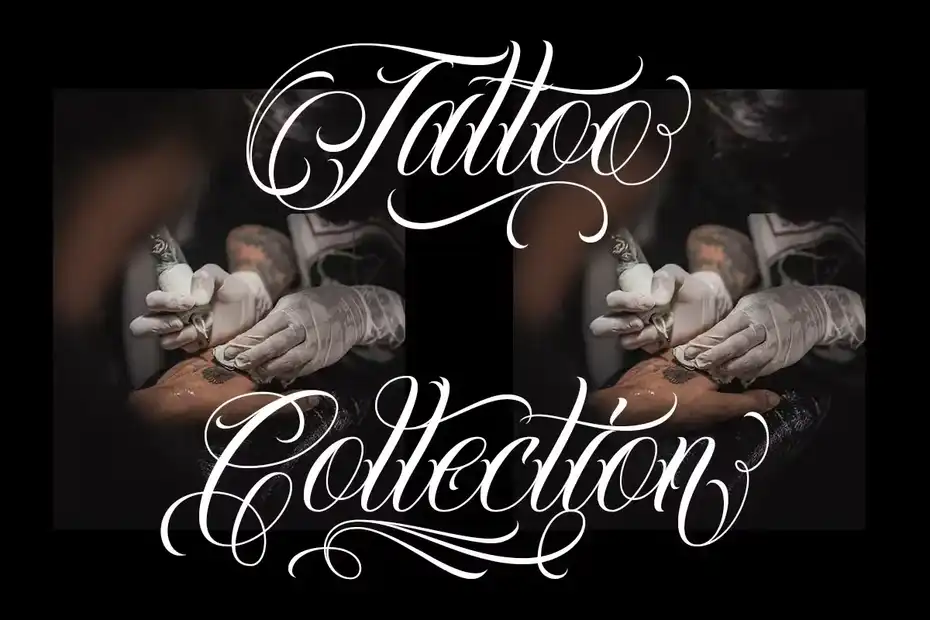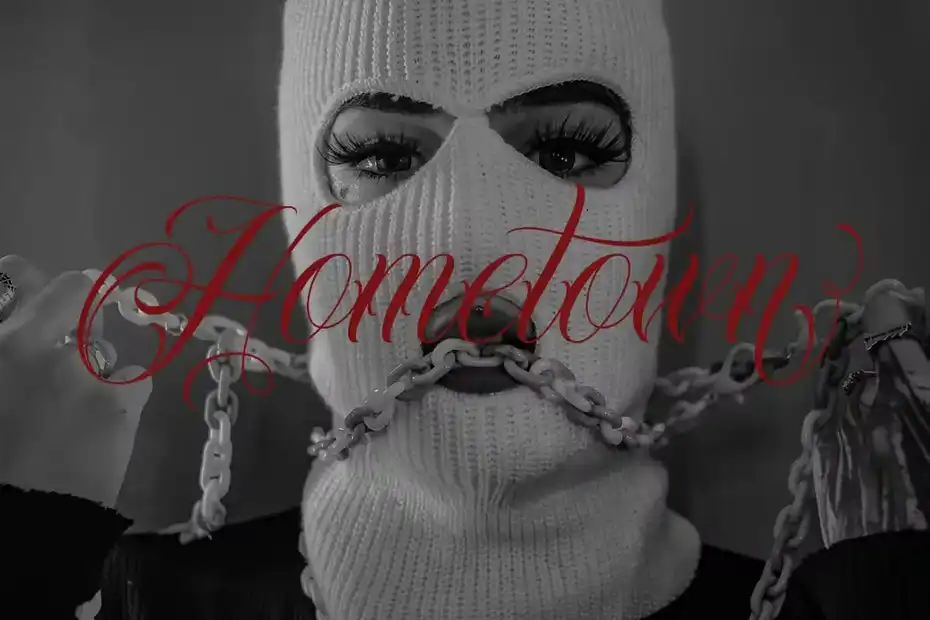
فونت انگلیسی تاتو Fearless | Tattoo Font : این مجموعه شامل یک فونت انگلیسی دست نویس است که برای تاتو، برندینگ، لوگو و غیره مناسب میباشد. اگر به فونت های حرفه ای و جذاب برای تاتو نیاز دارید، می توانید از بخش فونت انگلیسی برای تاتو در سیجی کوک به آرشیو کامل فونت های تاتو دسترسی داشته باشید و جذاب ترین فونت های تاتو را دانلود کنید.